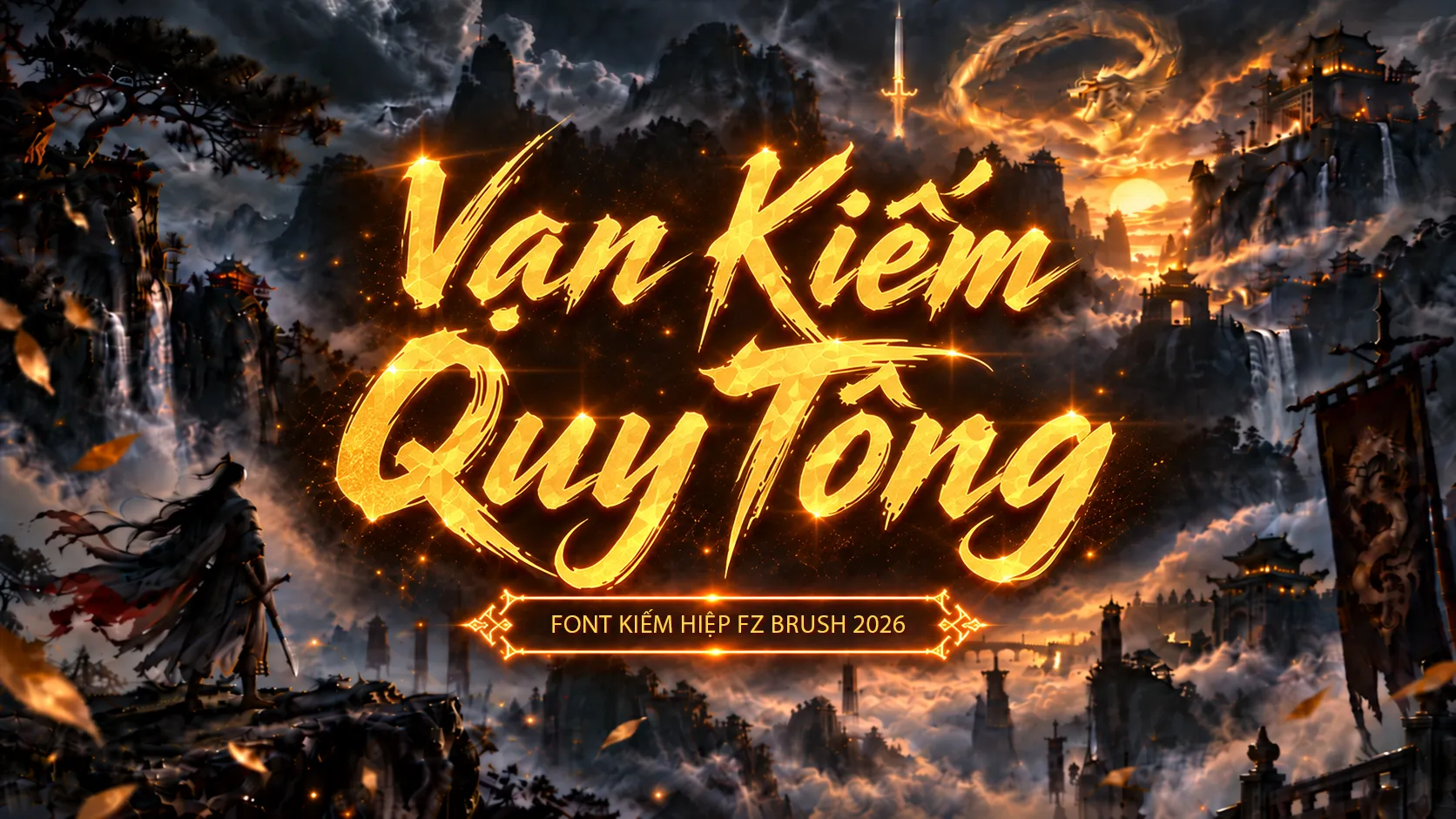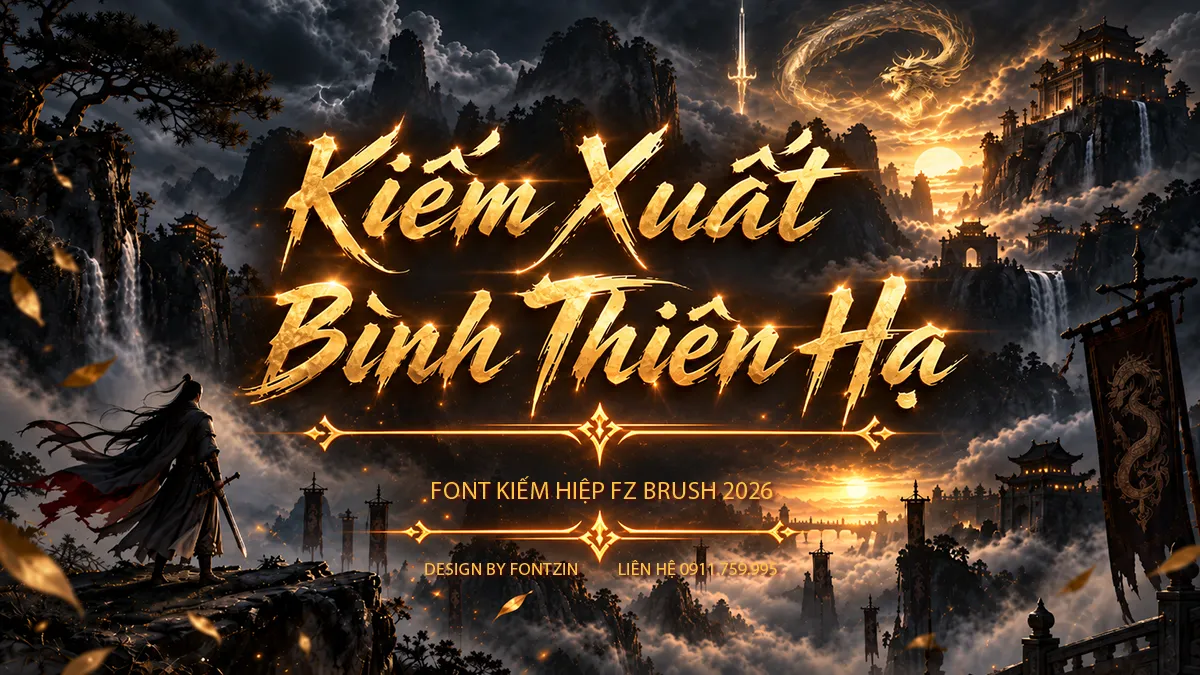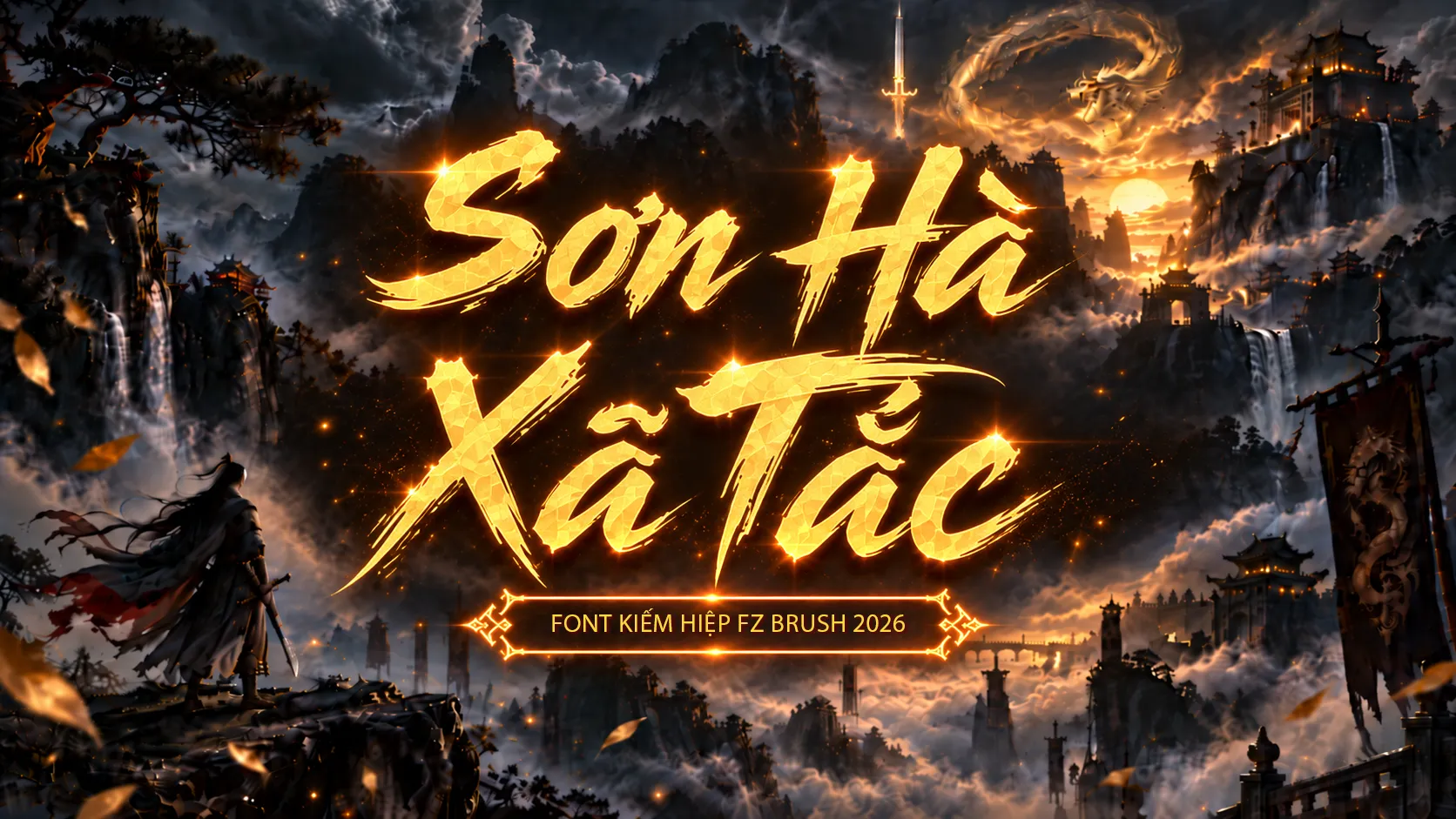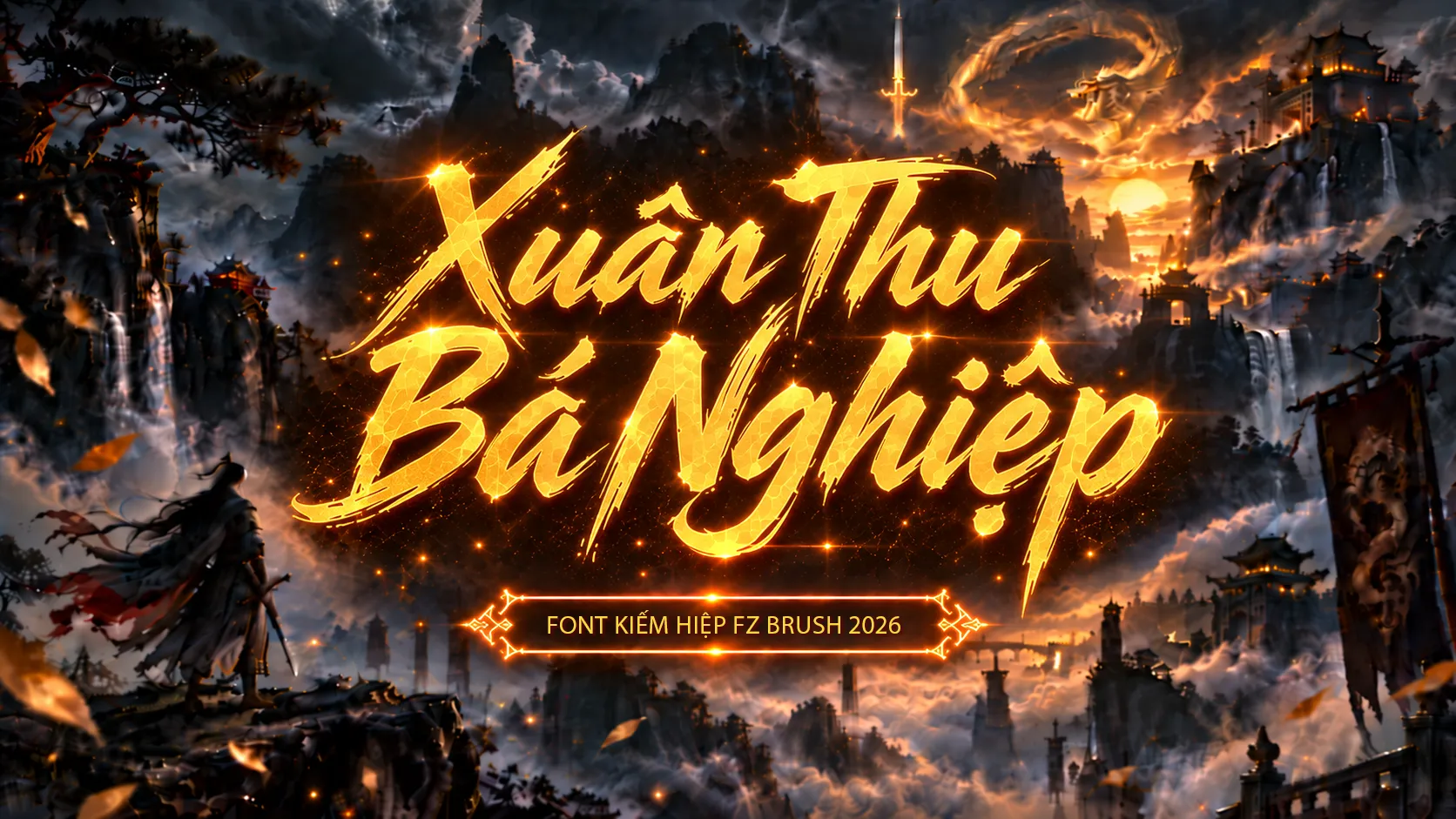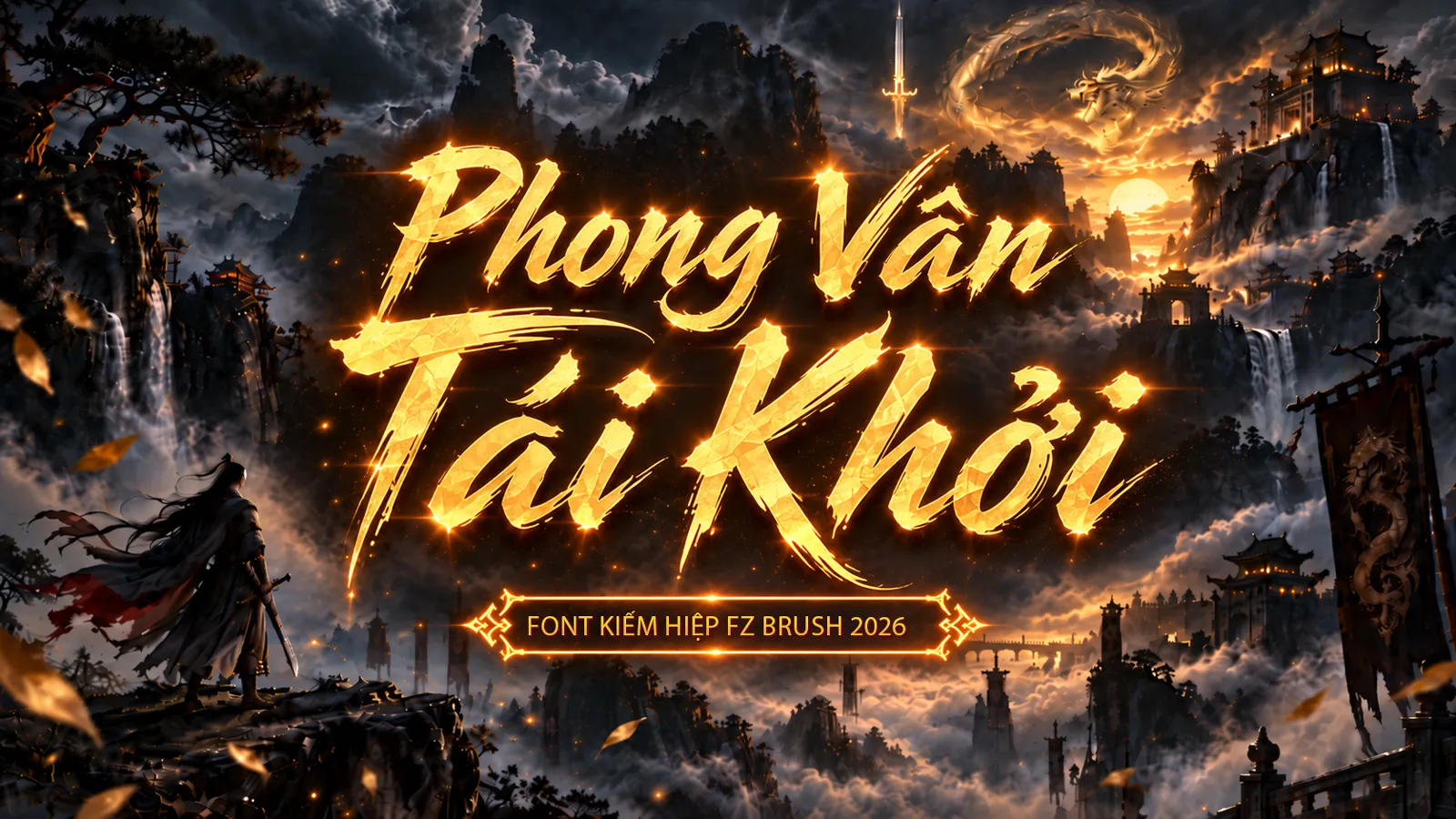
FZ Brush 2026 là mẫu font display được thiết kế dành cho những sản phẩm cần cảm giác mạnh mẽ, phóng khoáng và giàu chất võ hiệp. Lấy cảm hứng từ những nét cọ dứt khoát trong thư pháp kết hợp với ngôn ngữ hình ảnh của game kiếm hiệp, font tạo được cá tính rõ rệt ngay từ những dòng tiêu đề đầu tiên.
Điểm nổi bật của FZ Brush 2026 nằm ở những nét chữ sắc, dài, có độ vung và chuyển động tự nhiên. Khi đặt trên các background núi non, kiếm khí, cổ thành hay bối cảnh tiên hiệp, chữ dễ dàng trở thành tâm điểm của toàn bộ thiết kế.
FZ Brush 2026 – Font dành cho thế giới kiếm hiệp
Phong cách: Brush / Kiếm hiệp / Võ hiệp / Tiên hiệp / Game Fantasy
Không đi theo kiểu thư pháp truyền thống quá mềm mại, Font Game Kiếm Hiệp FZ Brush 2026 được xây dựng với cấu trúc chữ hiện đại hơn.
Các nét brush được xử lý theo hướng mạnh, nhanh và có lực. Một số nét kết thúc được kéo dài hoặc tạo đầu nhọn, mang lại cảm giác giống những đường kiếm được tung ra trong chuyển động.
Nhờ đó, font đặc biệt phù hợp với những câu chữ mang tính khí thế như:
- Kiếm Hiệp
- Kiếm Xuất Bình Thiên Hạ
- Vạn Kiếm Quy Tông
- Liên Minh Tranh Bá
- Thiên Hạ Vô Song
- Nhất Kiếm Giang Hồ
- Phong Vân Tái Khởi
- Long Tranh Hổ Đấu
Ở kích thước lớn, cá tính của font càng được thể hiện rõ.
Đặc điểm nổi bật của Font FZ Brush 2026
Nét brush mạnh nhưng vẫn rõ hình chữ
FZ Brush 2026 sử dụng ngôn ngữ tạo hình của chữ viết bằng cọ nhưng không phụ thuộc hoàn toàn vào texture brush.
Các nét chính có độ tương phản cao, phần đầu và cuối nét được xử lý sắc để tạo cảm giác chuyển động. Điều này giúp font giữ được vẻ phóng khoáng nhưng vẫn đủ rõ ràng khi sử dụng trong thiết kế thương mại.
Phù hợp với tiêu đề kích thước lớn
Đây là một display font, vì vậy hiệu quả nhất khi sử dụng cho headline, logo, poster hoặc tên sự kiện.
Trong các mẫu demo, những cụm chữ lớn như “Font Game Kiếm Hiệp” hay “Kiếm Xuất Bình Thiên Hạ” có thể chiếm phần lớn bố cục nhưng vẫn giữ được nhịp điệu và sự nổi bật.
Mang đậm không khí game võ hiệp – tiên hiệp
Hình dáng chữ được phát triển để phù hợp với nhiều bối cảnh quen thuộc của dòng game phương Đông:
Kiếm khí – giang hồ – môn phái – cổ thành – võ lâm – tiên giới – long khí – chiến trường – tranh bá.
Khi kết hợp với màu vàng kim, ánh sáng hoặc hiệu ứng glow, font tạo cảm giác như chữ được hình thành từ kiếm khí hoặc năng lượng.
Tuy nhiên, bản thân kiểu dáng chữ vẫn đủ mạnh để sử dụng với thiết kế đơn sắc.
Ứng dụng của Font Game Kiếm Hiệp FZ Brush 2026
FZ Brush 2026 có thể được sử dụng cho nhiều loại sản phẩm đồ họa, đặc biệt là các thiết kế cần một tiêu đề có cá tính mạnh:
- Logo và tên game kiếm hiệp.
- Banner quảng cáo game.
- Poster võ hiệp, tiên hiệp và fantasy.
- Thumbnail YouTube.
- Cover Facebook và social media.
- Tiêu đề phim hoặc video cổ trang.
- Tên nhân vật, môn phái và bang hội.
- Event trong game.
- Landing page game.
- Artwork kiếm hiệp.
- Packaging hoặc merchandise mang phong cách Á Đông.
- Key visual cho các chiến dịch truyền thông.
Font cũng phù hợp với những thiết kế không trực tiếp liên quan đến game nhưng cần cảm giác mạnh mẽ, tự do, tốc độ và chiến đấu.
Một font chữ được thiết kế để trở thành tâm điểm
Với FZ Brush 2026, chữ không chỉ đóng vai trò truyền tải nội dung.
Bản thân chữ có thể trở thành thành phần đồ họa chính của artwork.
Những nét kéo dài ở các ký tự lớn tạo nên đường dẫn thị giác tự nhiên. Khi bố trí đúng tỷ lệ, người thiết kế có thể sử dụng chính hình dáng của chữ để tạo chuyển động cho toàn bộ poster.
Đây cũng là lý do FZ Brush 2026 đặc biệt thích hợp với những thiết kế mà phần typography cần chiếm từ một phần ba đến một nửa diện tích hình ảnh.
Gợi ý phối màu cho FZ Brush 2026
Với chủ đề kiếm hiệp, một trong những cách thể hiện hiệu quả nhất là sử dụng tông:
Vàng kim + cam lửa + nền đen/xám lạnh.
Có thể kết hợp thêm Outer Glow hoặc ánh sáng nhẹ ở cạnh chữ để tạo hiệu ứng kiếm khí.
Một số phối màu khác cũng đáng thử:
Đỏ son + đen
Mang cảm giác chiến đấu, ma đạo hoặc huyết chiến.
Trắng bạc + xanh lam
Phù hợp với kiếm khí, băng hệ và tiên hiệp.
Vàng đồng + nâu cổ
Thích hợp với phong cách võ lâm cổ điển.
Trắng + đen
Tập trung hoàn toàn vào hình dáng và nét brush của font.
FZ Brush 2026 và dấu tiếng Việt
Một điểm quan trọng đối với font dành cho thị trường Việt Nam là cách các dấu thanh tương tác với hình dáng chữ.
Qua các mẫu như “Kiếm Hiệp” và “Kiếm Xuất Bình Thiên Hạ”, hệ thống dấu được bố trí theo hướng hòa vào chuyển động của nét chữ thay vì trở thành những chi tiết tách biệt.
Điều này đặc biệt quan trọng với font brush, bởi dấu quá nhỏ hoặc đặt không hợp lý có thể phá vỡ nhịp điệu của toàn bộ từ.
FZ Brush 2026 được định hướng để vừa giữ được cá tính của font, vừa phù hợp với những tiêu đề tiếng Việt có nhiều dấu.
FZ Brush 2026 là một thử nghiệm kết hợp giữa brush lettering hiện đại và tinh thần của typography game kiếm hiệp.
Từng nét chữ được định hướng theo phong cách sắc, mạnh và giàu chuyển động, phù hợp với những thiết kế muốn tái hiện không khí giang hồ, võ lâm và tiên hiệp phương Đông.
Nếu bạn đang tìm kiếm một font chữ để tạo tiêu đề game, poster kiếm hiệp hoặc những artwork cần một typography có cá tính mạnh, Font Game Kiếm Hiệp FZ Brush 2026 là một lựa chọn đáng để trải nghiệm.